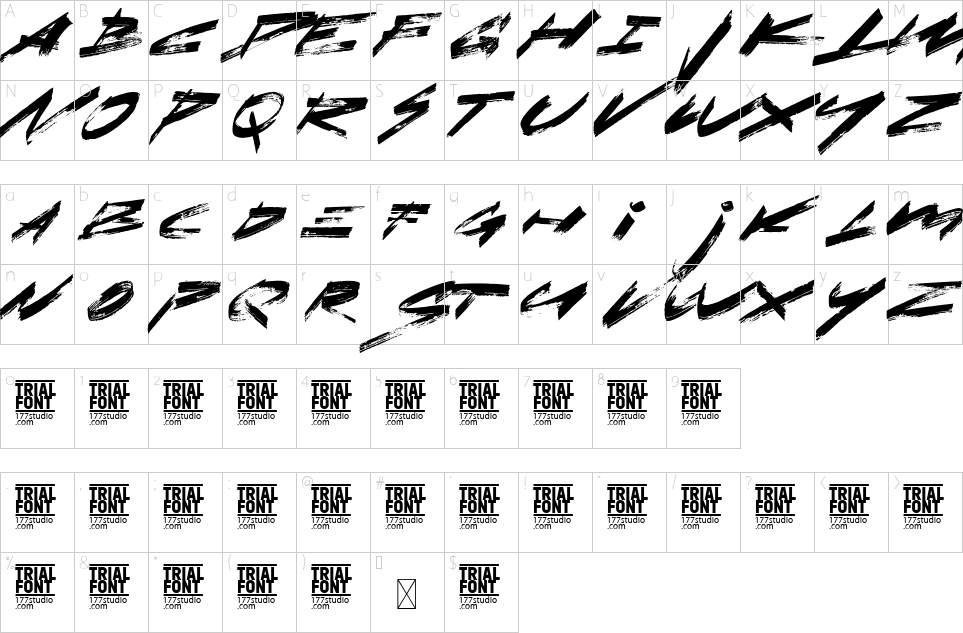
A fonte Across Before é uma opção atraente para designers gráficos e criadores de conteúdo online em busca de uma opção de fonte de alta qualidade. Ela foi projetada pelo estúdio de design 177studio.com e é adequada tanto para dispositivos Windows quanto para Mac. Com seu design único, Across Before oferece uma solução elegante para qualquer projeto de design. O fato de ser um recurso de fonte gratuita faz com que ela seja ainda mais atrativa, permitindo que designers tenham uma fonte versátil sem precisar gastar nada extra. Com mais de 150 downloads, é evidente que muitos utilizam a Across Before, o que a torna uma escolha segura e confiável para qualquer projeto. Se você está procurando uma fonte profissional e de alta qualidade que não exige nenhuma cobrança extra, Across Before pode ser uma ótima escolha para você.